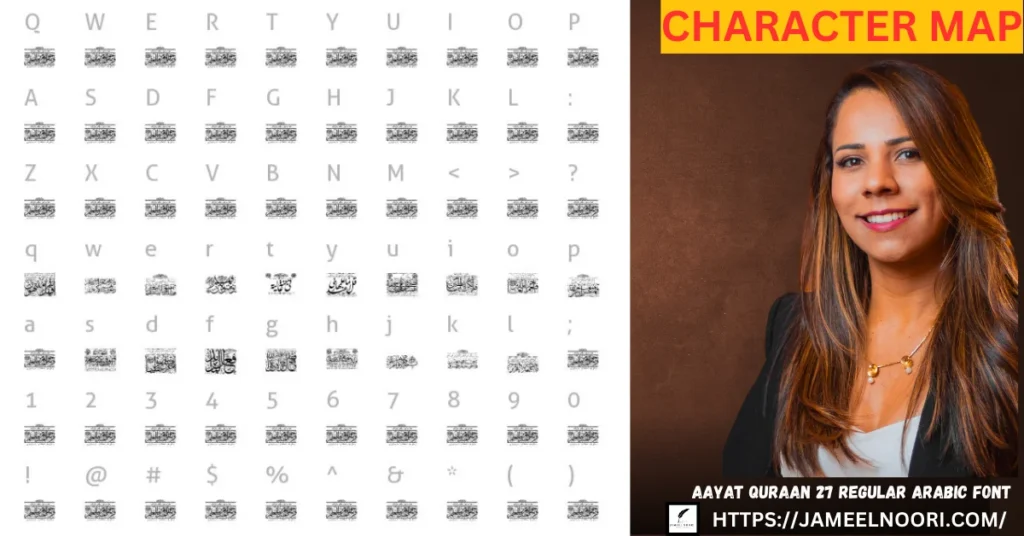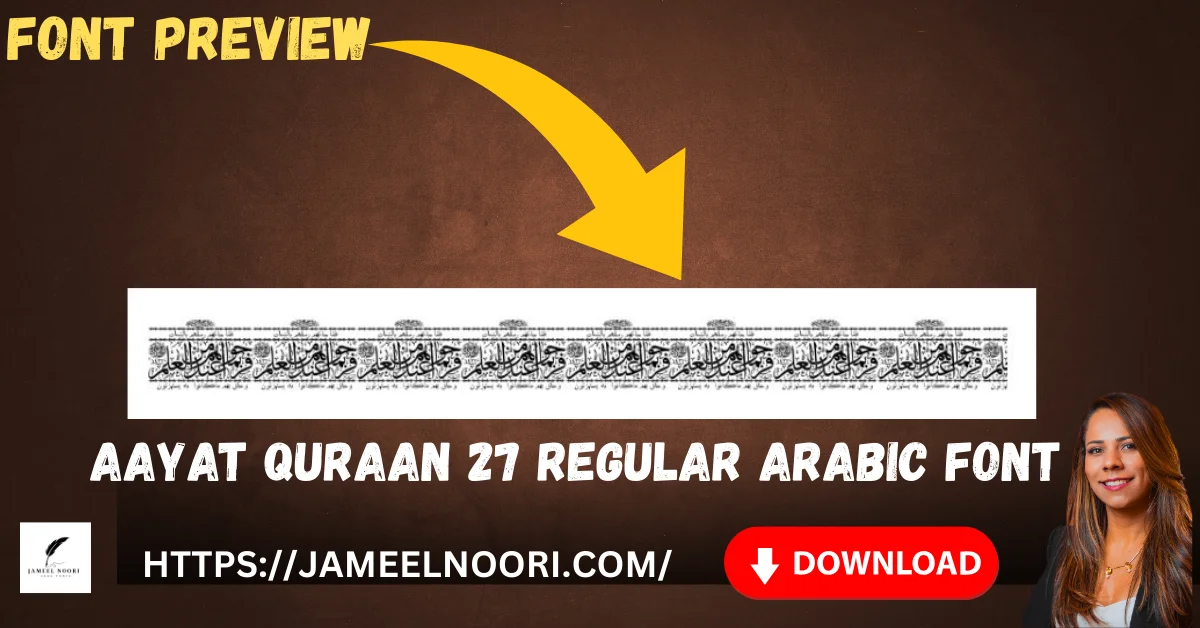
Features of Aayat Quraan 27 Regular Arabic Font
Why Choose Aayat Quraan 27 Regular Arabic Font
Aayat Quraan 27 Regular Arabic Font select karne ke kuch important reasons ye hain:
- High Readability: Text ko easily read kiya ja sakta hai.
- Professional Calligraphy: Quranic aur Arabic style me perfect design.
- Multi-purpose Use: Websites, PDF, print aur Urdu fonts projects me use ho sakta hai.
Aayat Quraan 27 Regular Arabic Font for Designers
Designers aur Urdu fonts lovers ke liye Aayat Quraan 27 Regular Arabic Font ek must-have option hai. Ye font:
- Projects me professional look deta hai.
- Arabic calligraphy aur Quranic text ke liye best fit hai.
- Print aur digital media dono me easy integration hota hai.
Advantages of Using Aayat Quraan 27 Regular True Type Arabic Font
- Elegant Design: Quranic aur Urdu calligraphy ke liye perfect.
Tips to Use Aayat Quraan 27 Regular TTF Arabic Font Efficiently
- Combine with Urdu Fonts: Best readability ke liye.
- Use in Headings & Subheadings: Blogs aur articles me.
- Check Character Map: Calligraphy ka sahi use ensure karne ke liye.
Aayat Quraan 27 Regular Arabic Font Pakistan ke designers, students aur Urdu fonts lovers ke liye ek ultimate choice hai. Is font ka professional look, easy installation aur high readability isay best Arabic font banata hai. Agar aap apne projects me Quranic aur Arabic calligraphy ka authentic touch dena chahte hain, to ye font definitely try karna chahiye.
Is this font suitable for Quranic text?
Yes, it is professionally designed for Quranic and Arabic calligraphy.